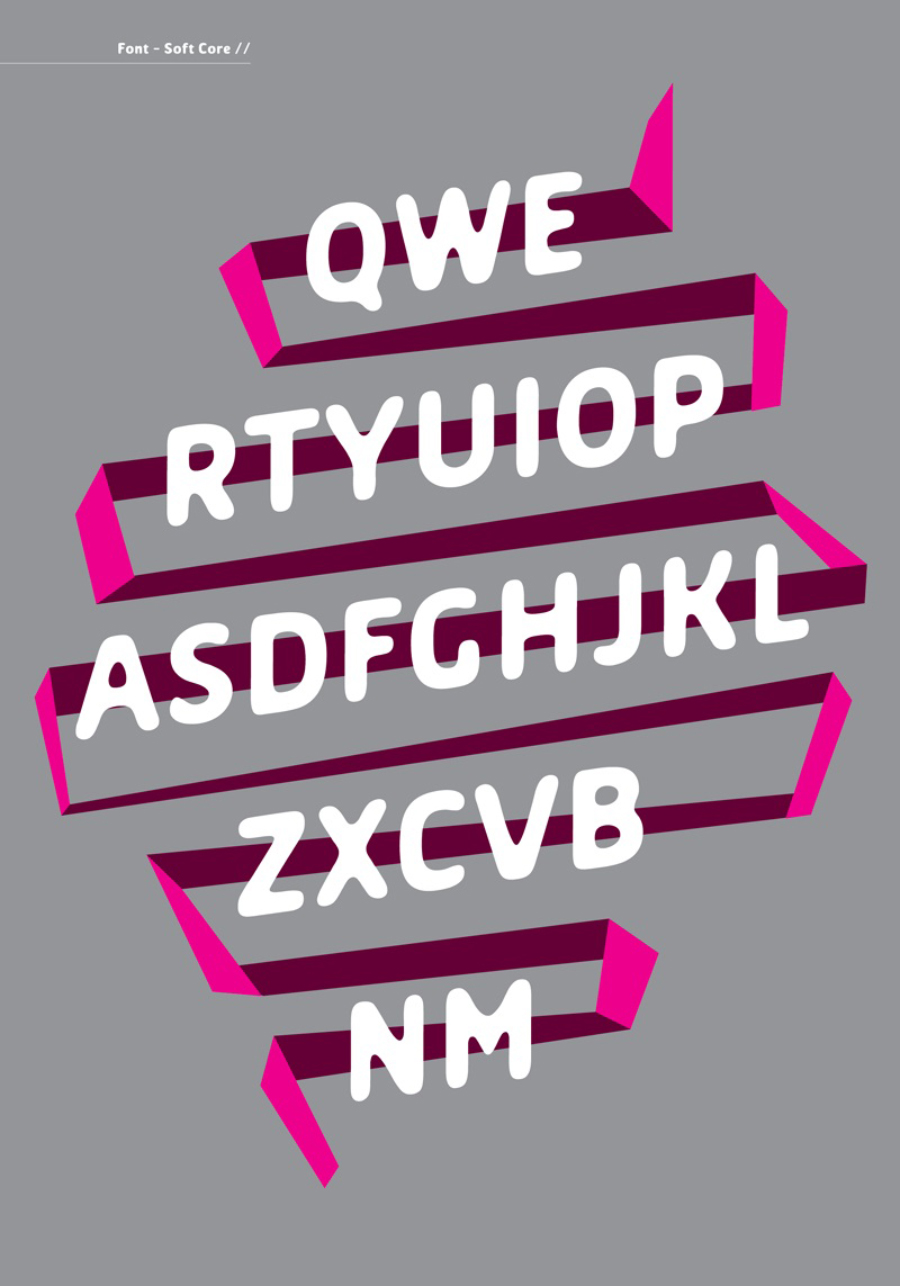
软核自由字体
Soft Core Free Typeface是Ungrund Studio的“Core”字体的圆形版本。这种俏皮的显示sans-serif可以很好的为许多不同类型的设计工作。正如我们在预览中看到的那样,Soft Core是一个有趣的海报设计的正确选择,但对于其他作品(如品牌和徽标)也是非常好的选择。